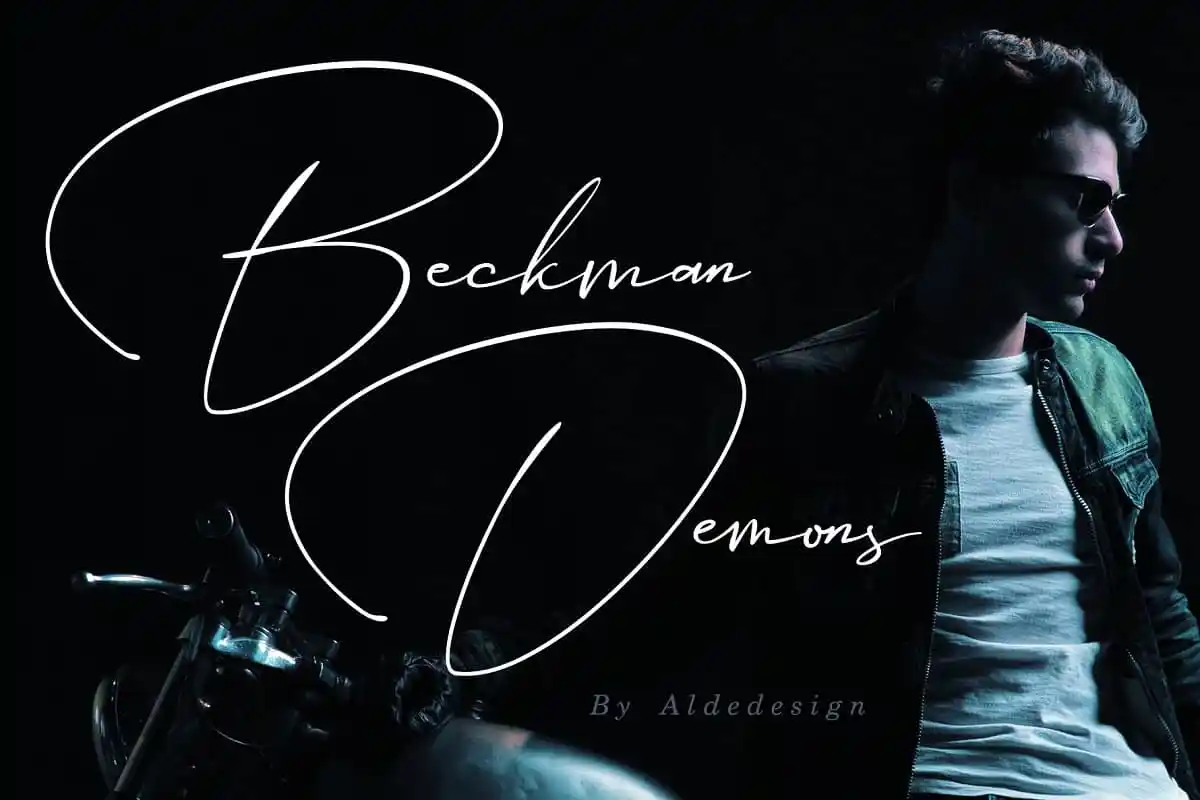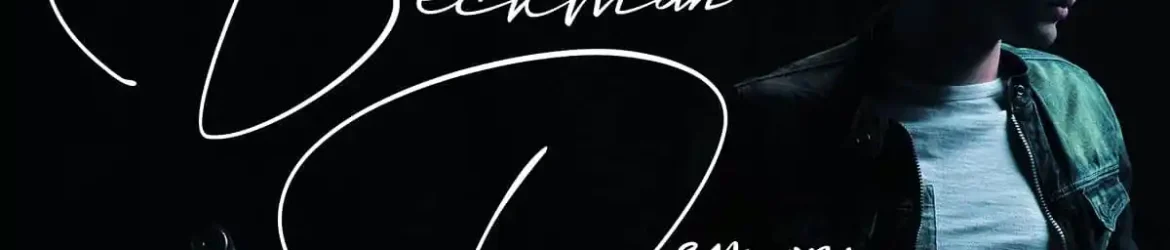
Beckman Demons Signature Font – Download Grátis
A ‘Beckman Demons Signature Font’ é uma elegante escolha para qualquer projeto que exige estilo sofisticado. Essa tipografia foi criada pelo designer Aldedesign e traz um toque moderno, inspirado nas fotografias contemporâneas. Perfeita tanto para criar watermark em suas fotos quanto para personalizar cartões de convite ou materiais de marcação, esta fonte tem a capacidade de tornar qualquer texto único e elegante. Seu uso fácil permite que você adicione um toque final sofisticado aos seus projetos, seja na criação de uma assinatura profissional, em documentos corporativos ou em material de marketing. Essa é uma ótima opção para aqueles procurando um visual atraente e minimalista para seus projetos digitais.